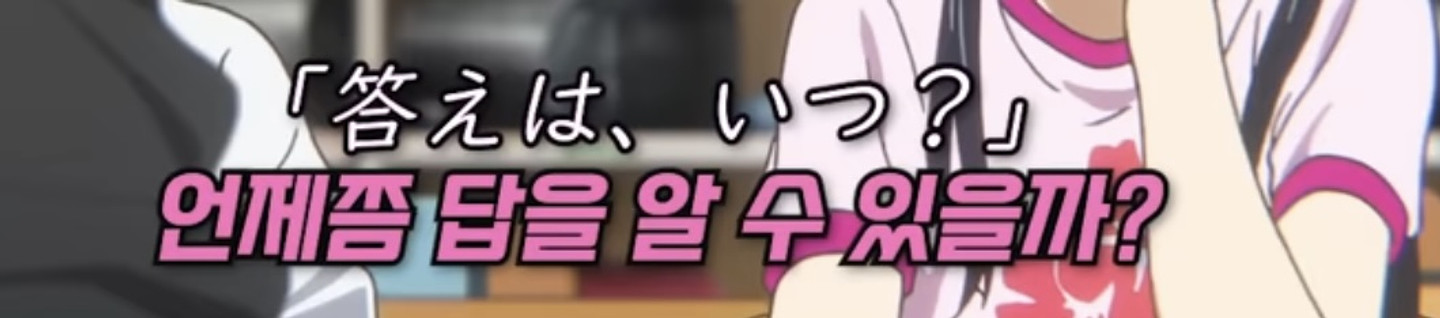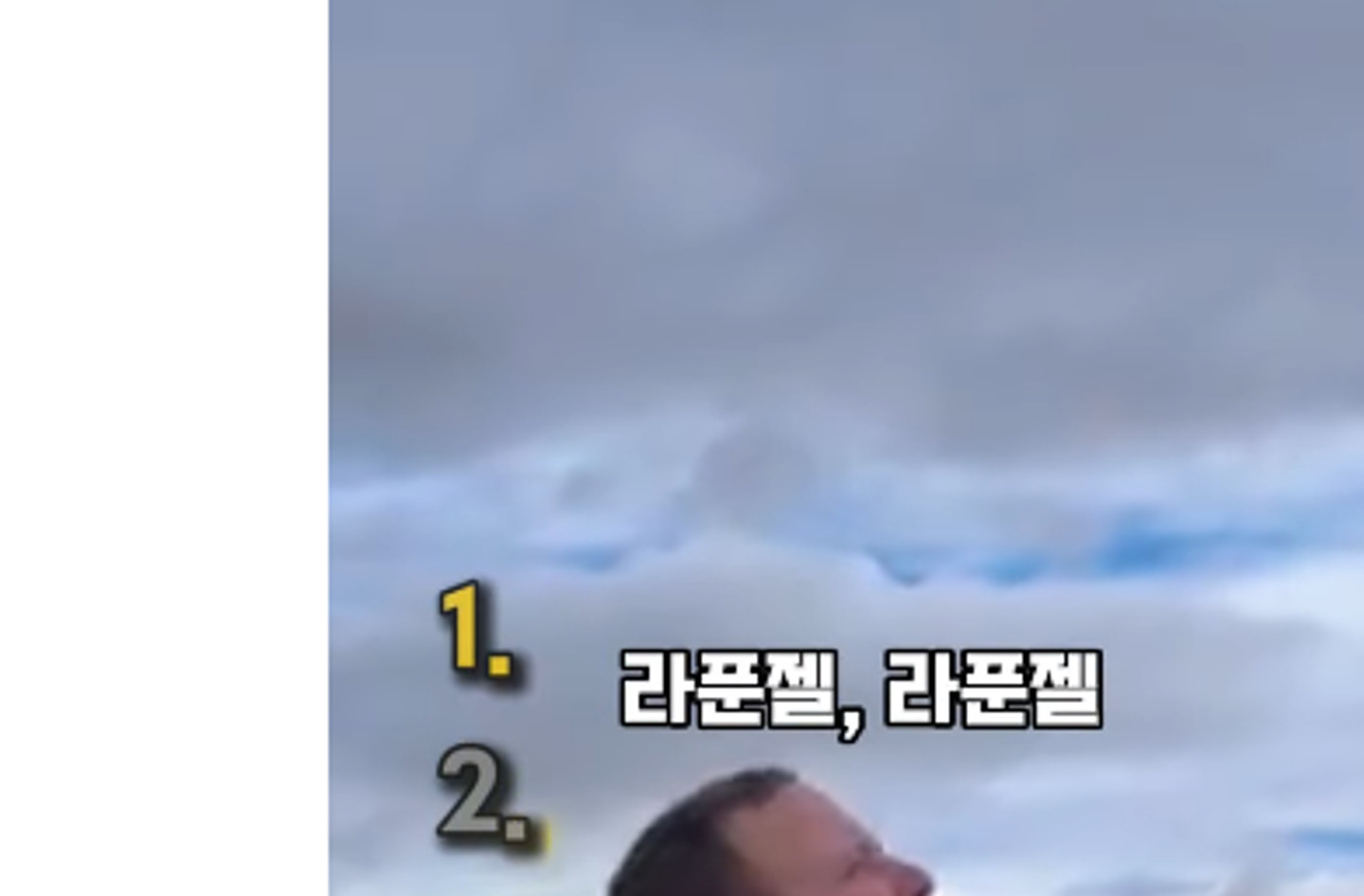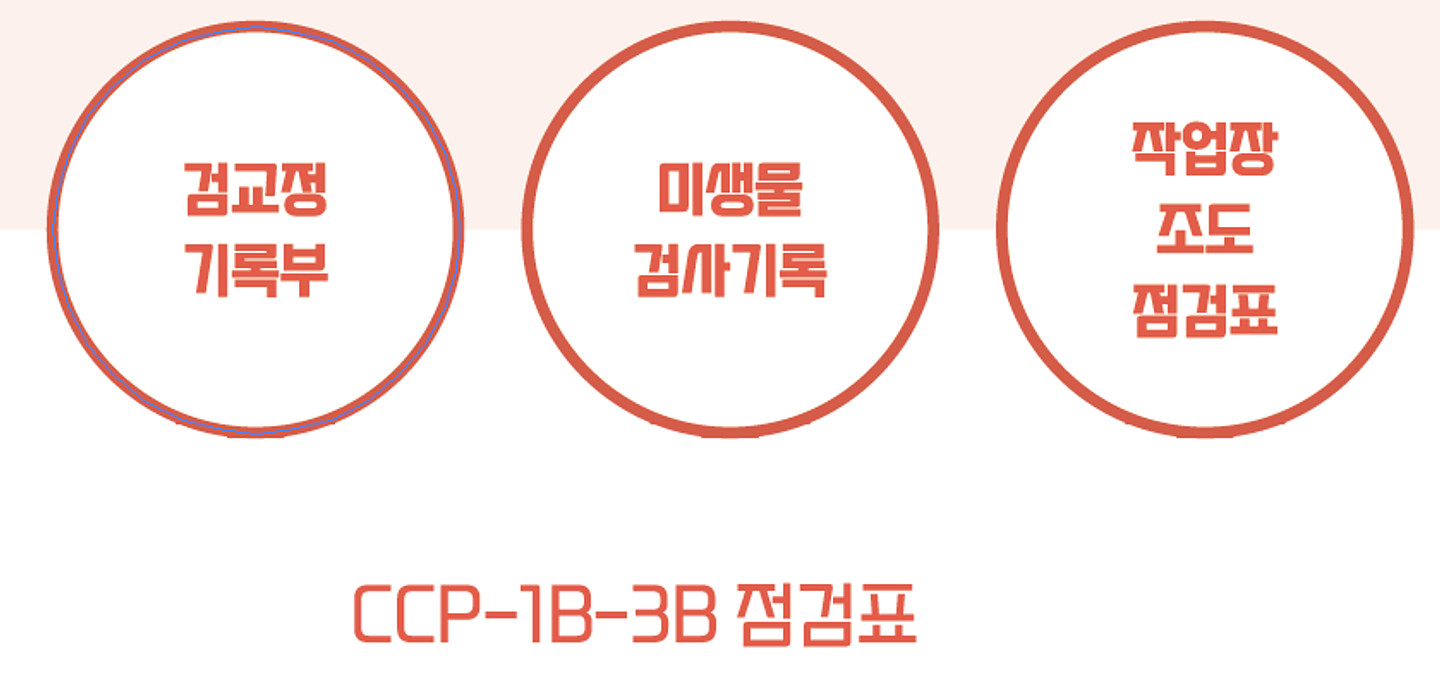
세방고딕
Sebang Gothic
作成者 Sebang Group
スタイル ゴシック
セバン グループ創立 55 周年を迎え、セバン グループ フォントを開発しました。
SEBANG グループ社のアイデンティティを込めたフォントで、個人、企業などすべてのユーザーが自由に使用できるフォントです。